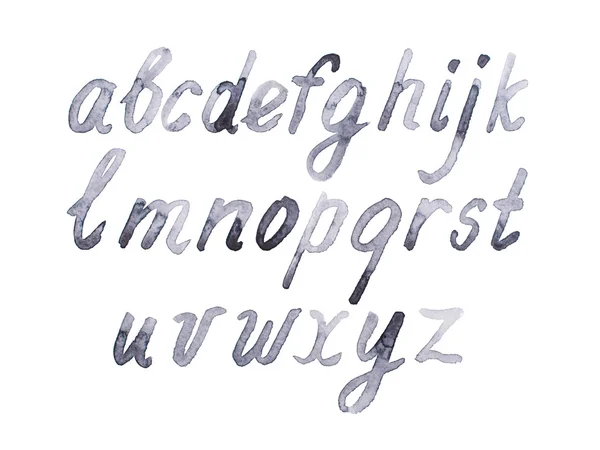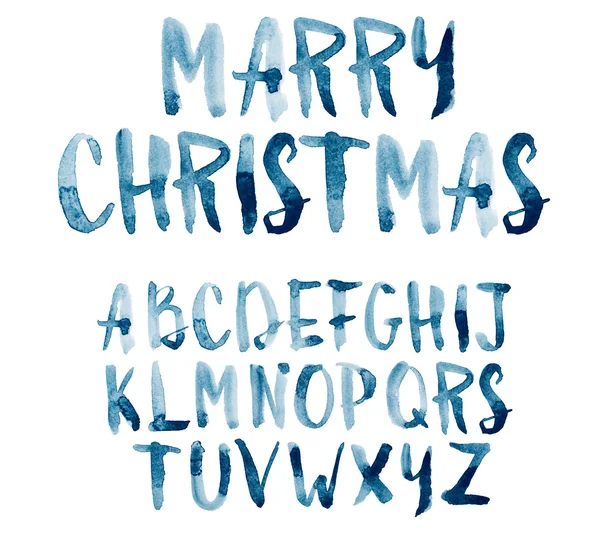
Текст акварелью в Adobe Photoshop
В этом уроке мы будем создавать реалистичный текст, написанный акварелью в Adobe Photoshop. В начале урока вы найдете все необходимые исходники, которые мы будем использовать в уроке. Нам предстоит работать с режимами наложения, стилями слоя и обтравочными масками. Также в уроке вы найдете набор бесплатных акварельных текстур, с помощью которых сможете добиться разных вариантов эффекта.
Результат
Для начала создайте новый документ, установите акварельный шрифт и введите свой текст.
Создайте новый слой и вставьте в него акварельную текстуру. Поместите этот слой над слоем с текстом.
Кликните правой кнопкой по слою с текстурой и выберите Create Clipping Mask/Создать обтравочную маску.
Укажите слою с текстом следующие стили слоя:
Inner Glow/Внутреннее свечение
Stroke/Обводка
Дублируйте текстовый слой вместе со слоем с текстурой и немного переместите копии, чтобы получилось примерно как на скриншоте ниже. Снизьте Opacity/Непрозрачность примерно до 50%. Вы также можете убрать для копии стиль слоя Stroke/Обводка, чтобы получить более мягкий результат.
Чтобы добавить реалистичности эффекту, добавьте пятен краски, используя фигуры подтеков и пятен. Используйте снова акварельную текстуру в качестве обтравочной маски, чтобы сделать брызги акварельными.
При желании вы можете украсить работу, добавив текст от руки или нарисованные узоры. В нашем примере использованы зарисовки и черная акварель в режиме наложения Multiply/Умножение. Чтобы получить схожий результат, вам понадобится два корректирующих слоя Brightness/Contrast /Яркость/Контраст.
Мы также добавили текст используя рукописный шрифт. Также вы можете добавить одну из бесплатных акварельных текстур в режиме Multiply/Умножение на 50% непрозрачности.
Результат
Инструкция по преобразованию фото в реалистичную акварельную живописьРанее я рассказывала о том, как можно превратить фото в акварельный рисунок, выполненный мелкими и средними мазками.
Сегодня хочу познакомить вас с новой техникой «акварельной живописи» в Photoshop, которая мне очень понравилась, и уверена, не оставит равнодушной и вас!
Такой эффект отлично подойдет для обработки свадебного фото. Акварельный рисунок, выполненный по вашему фото можно распечатать на холсте и никто даже не догадается, что это творение цифровой, а не настоящей кисти мастера.
Я буду обрабатывать вот такое фото.
Шаг 1.
Сделайте дубликат слоя с фото (cmd + J или ctrl + J).
Назовите его Фото.
Щелкните правой клавишей мыши по слою Фото и выберите пункт Создать смарт – объект.
Шаг 2.
Щелкните по слою Фото и выберите Фильтры – Галерея фильтров – Имитация — Сухая кисть.
Установите следующие параметры.
- Размер кисти – 3
- Детализация – 8
- Текстура — 1
Вы можете выбрать другие значения в зависимости от разрешения вашего фото и качества. Мазки должны быть заметны, но не ярко выражены.
Шаг 3.
Выберите для слоя Фото Фильтры – Галерея фильтров – Имитация – Аппликация.
Установите следующие параметры:
- Количество уровней – 7
- Простота краев -2
- Четкость краев – 3
Здесь нужно сделать так, чтобы читался свето-теневой рисунок, но контуры объекта не пострадали.
Получится вот такая схема со слоями
Удобство использования смарт объектов состоит в том, что после применения фильтров можно редактировать их настойки:
- Настройки самого фильтра, щелкнув дважды по названию фильтра. В нашем случае это Галерея фильтров в обоих случаях. Последний примененный фильтр выводится вверху списка.
- Настройки параметров наложения слоя с фильтром. На рисунке выше значок обозначен красным цветом.